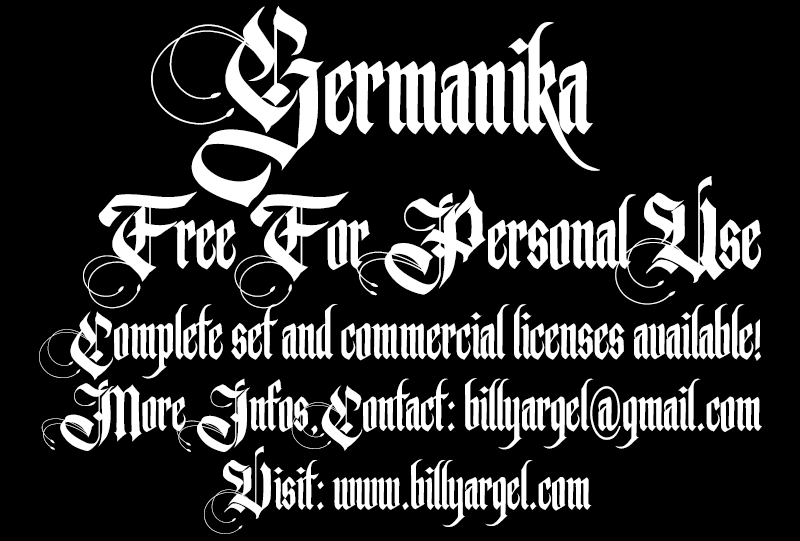
A Germanika Font é uma escolha perfeita para designers que valorizam o estilo gótico moderno e sofisticado. Desenhada pelo talentoso Hamilton, esta fonte possui um caráter elegante e versátil, ideal tanto para criações digitais quanto para impressões em papel. Com seu design gótico inspirado, a Germanika oferece linhas levemente inclinadas e detalhes sutis que proporcionam profundidade aos textos. Esta fonte é especialmente adequada para trabalhos profissionais que buscam uma estética única e respeitável, seja em materiais impressos ou na web. Como parte de sua natureza partilhável e gratuita, esta fonte é perfeita para uso pessoal sem necessidade de licenciamento adicional. Para quem busca mais recursos ou um conjunto completo da Germanika, a equipe de Hamilton está disponível através do site @billyargel.com para fornecer mais detalhes sobre as opções disponíveis. Se você é um designer em constante busca por novas fontes e estilos góticos que complementem sua obra, a Germanika Font pode ser uma excelente escolha. Confortável tanto para textos simples quanto para capítulos de livros ou títulos destacados, ela certamente se encaixa perfeitamente em qualquer projeto. Para maiores detalhes e informações, visite o site @billyargel.com.